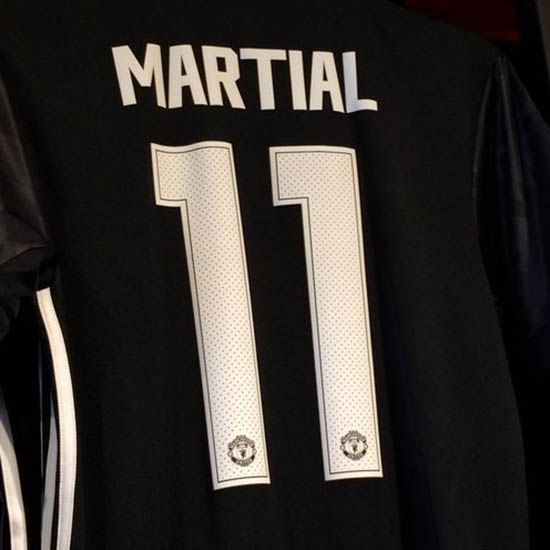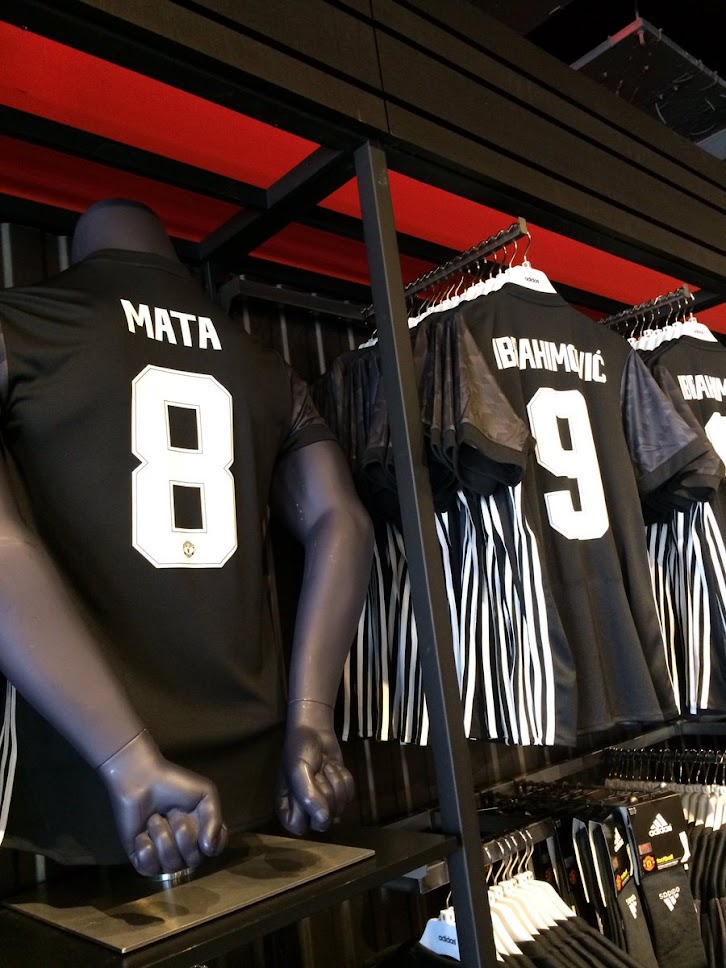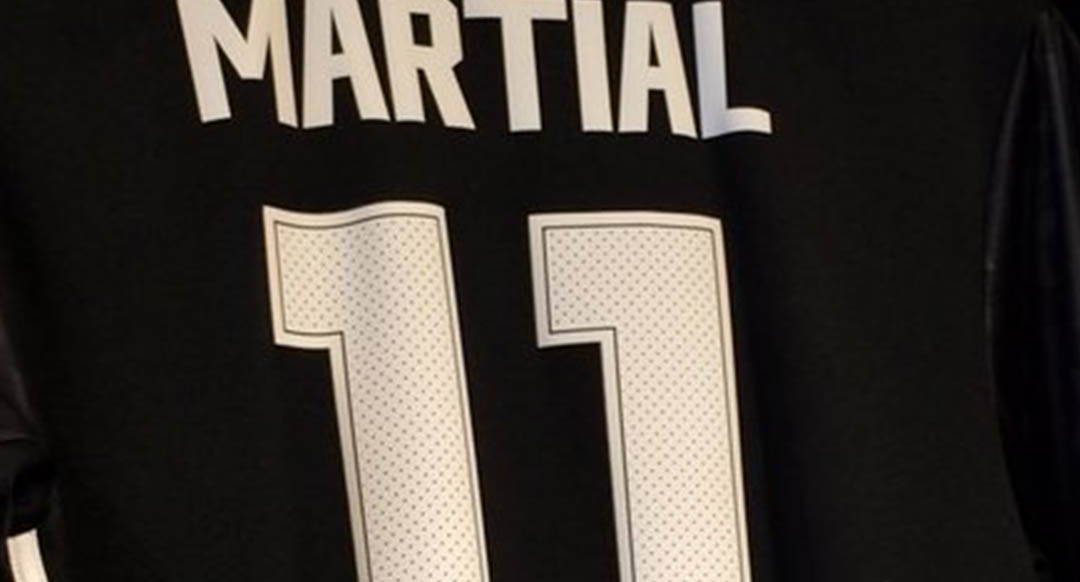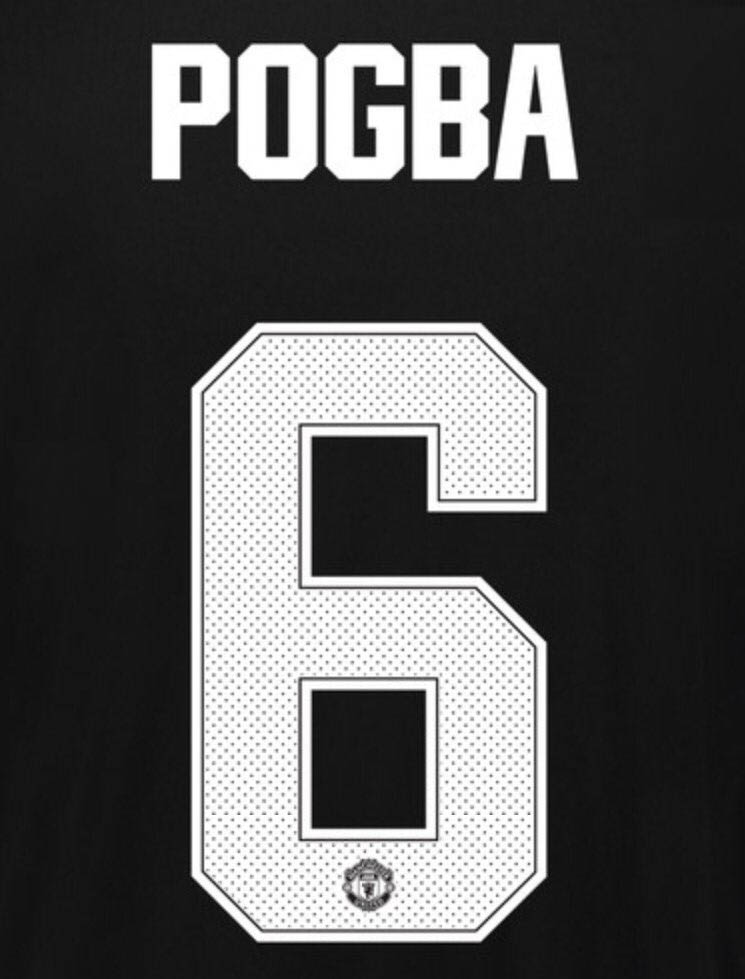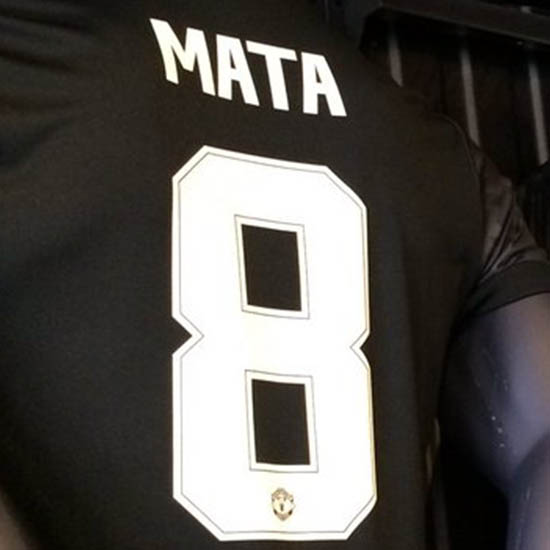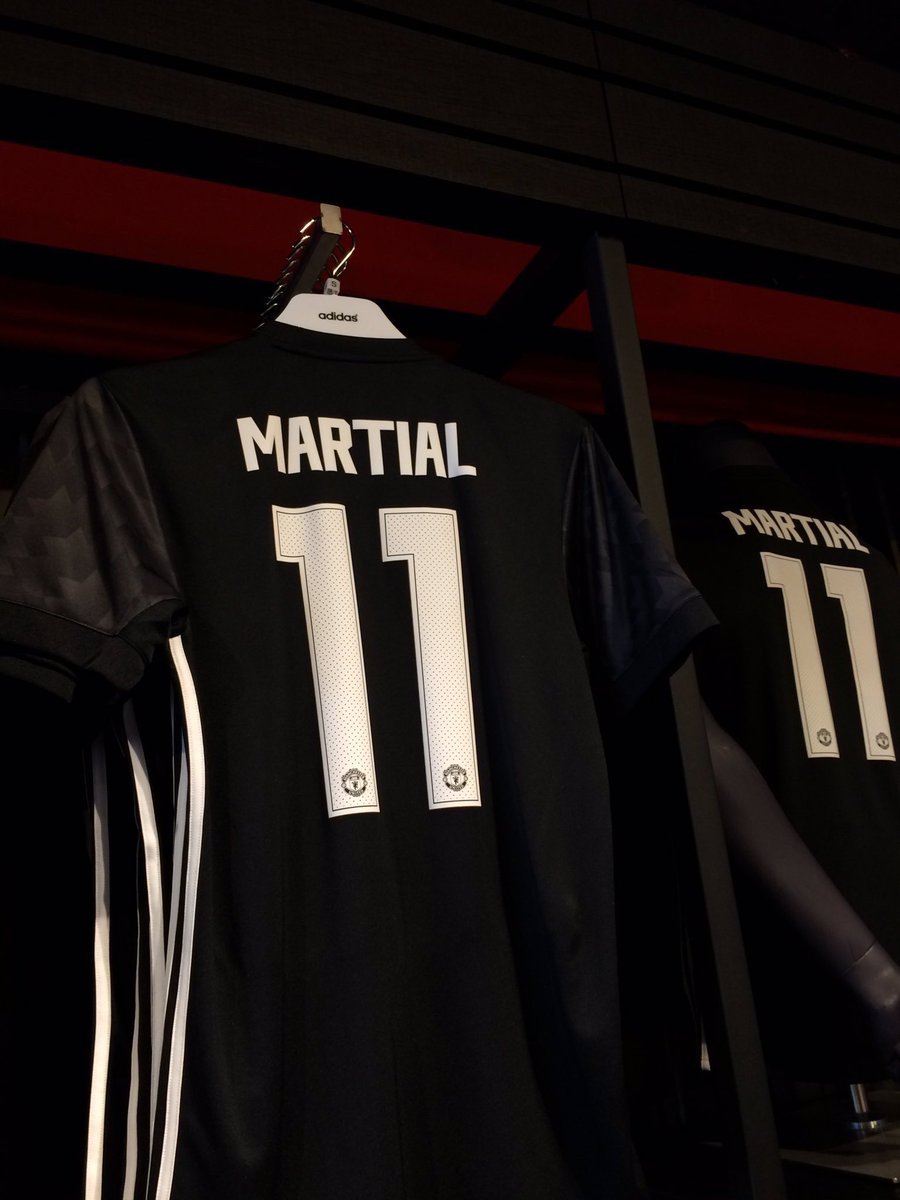
Völlig neue Manchester United 17-18 Trikot-Schriftart enthüllt
Der englische Premier-League-Gigant Manchester United wird in der 2017-18 Premier League Saison nicht nur eine völlig neue Schriftart tragen - der Klub wird in seinen 2017-18 Pokalspielen ebenfalls eine neue Schriftart haben.
Manchester United 2017-18 Pokalschriftart
Hier ist die neue ManU 17-18 Pokalschriftart.
Die neue Manchester United 17-18 Trikot-Schriftart weist ein deutlich abgewinkelteres Design als die neue Premier-League-Schriftart für die Saison 2017-18 auf. Tatsächlich ist der Stil der neuen Manchester United Schriftart der NFL-Schriftart ähnlich.
ManUs neue 2017-18 Trikot-Schriftart für Pokalspiele setzt am unteren Ende auf ManUs Wappen.